10款高质量英文组合字体
还在为字体搭配犯愁吗?一个成功的设计作品,字体组合的功劳不容小觑。素材君精选了10款高质量的英文组合字体,帮助你轻松打造出既有视觉冲击力又兼具出色可读性的作品。
Excmaros
拥有纯正的手工毛笔质感,笔触流畅自然,极具艺术表现力。非常适合用于签名、文具设计、品牌徽标、字体引言、网站标题以及各种品牌推广材料,能为您的项目增添独特的优雅和个性。
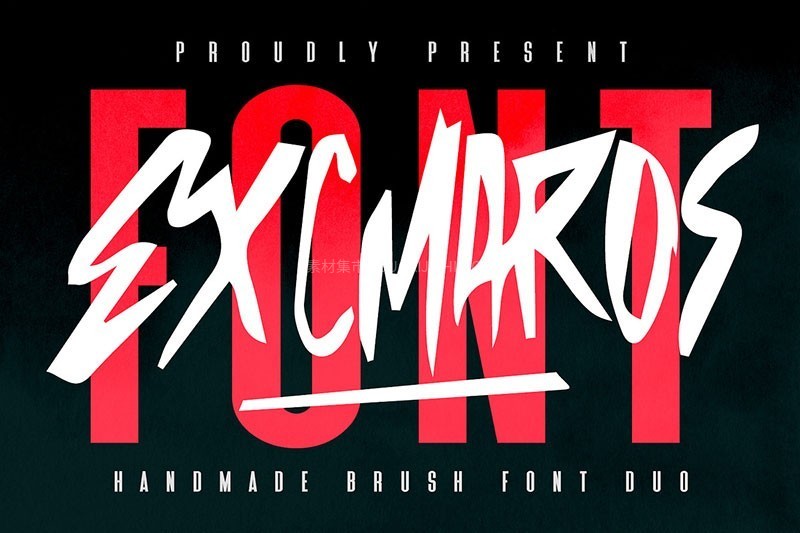
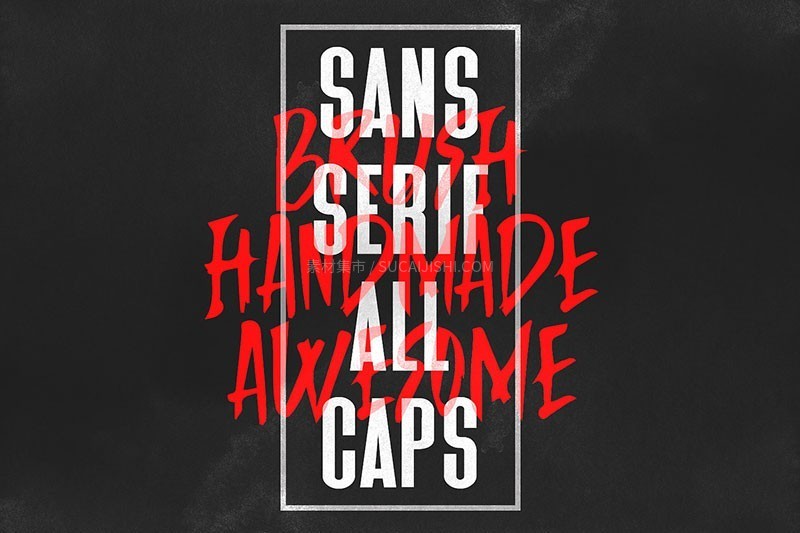
Morthano
一款俏皮的组合字体,将活泼的活力与现代的多功能性完美融合。Morthano 大小写字母是两种风格,将趣味、创意和风格融为一体,浑然一体。Morthano 非常适合品牌推广、包装、海报、社交媒体图形、儿童项目以及任何需要友好、乐观基调的场合,它能为任何视觉呈现瞬间注入活力。
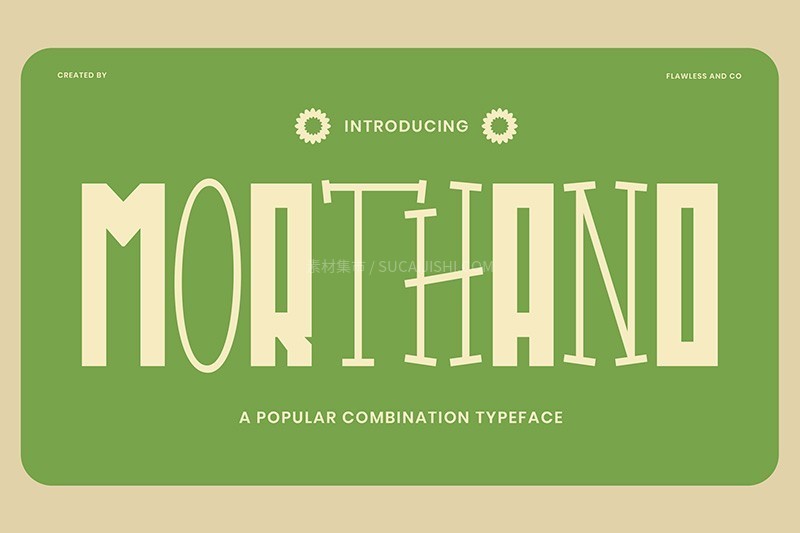
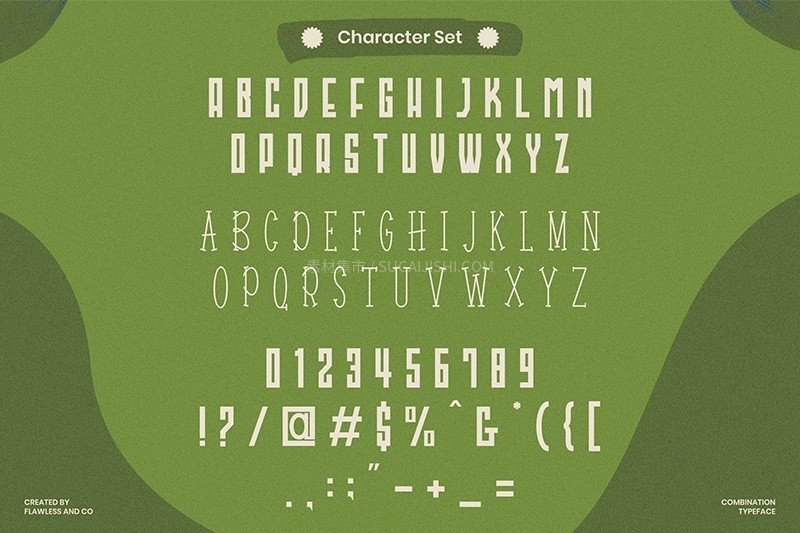
Nineties Party Club
一款大胆的复古字体组合,融合了醒目的无衬线字体和粗体、充满活力的文字。这种强大的组合营造出一种趣味十足的怀旧氛围,非常适合那些以复古风格吸引眼球的设计。
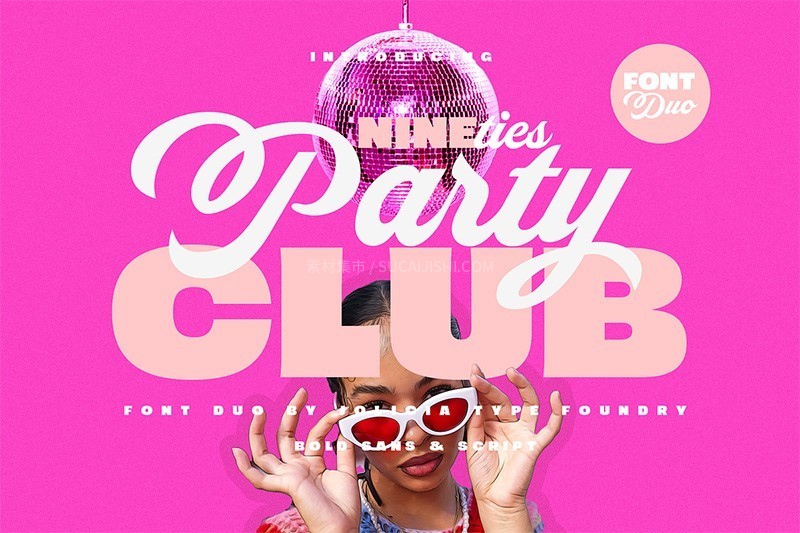
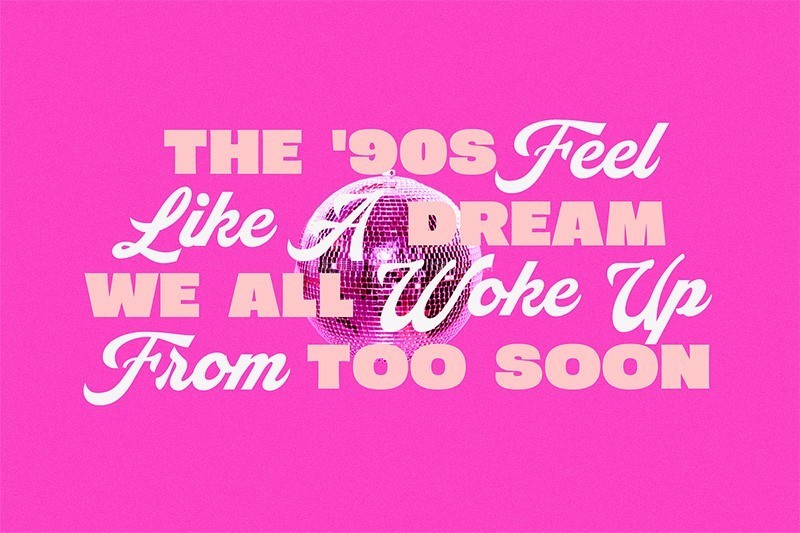
Gatsby Prelude
一款高大字体组合,巧妙融合了装饰艺术风格的无衬线体和单线体。这套字体组合用途广泛,用于从标识到婚礼请柬,也非常适合品牌推广和引言,能为您的设计增添独特的复古魅力。
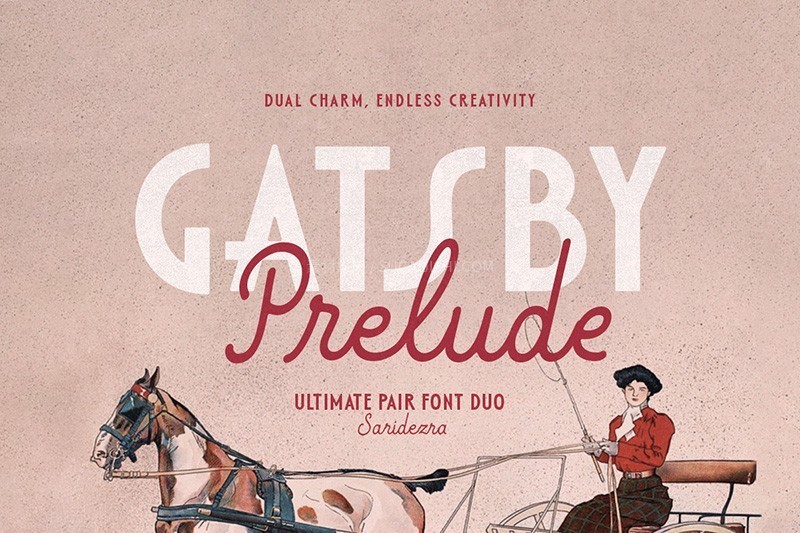
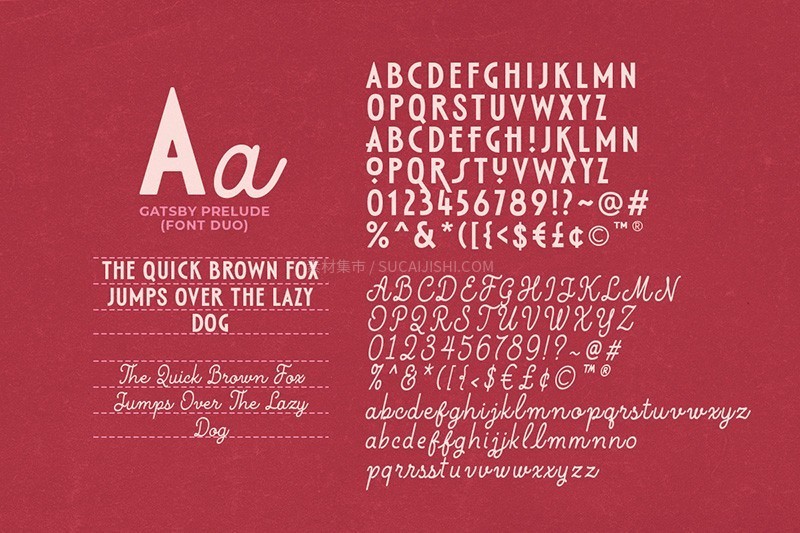
Folkies Vantage
Folkies Vantage 字体粗犷,复古纹理,边缘做旧,营造出一种年代感和灵魂感。它非常适合用于标签、T 恤印花、咖啡馆菜单、标识、乡村风包装以及怀旧设计主题。无论您是为复古牛仔品牌、手工酿造咖啡店还是本地摩托车修理厂创作,这款字体都能以原始的手工质感提升您的品牌形象。
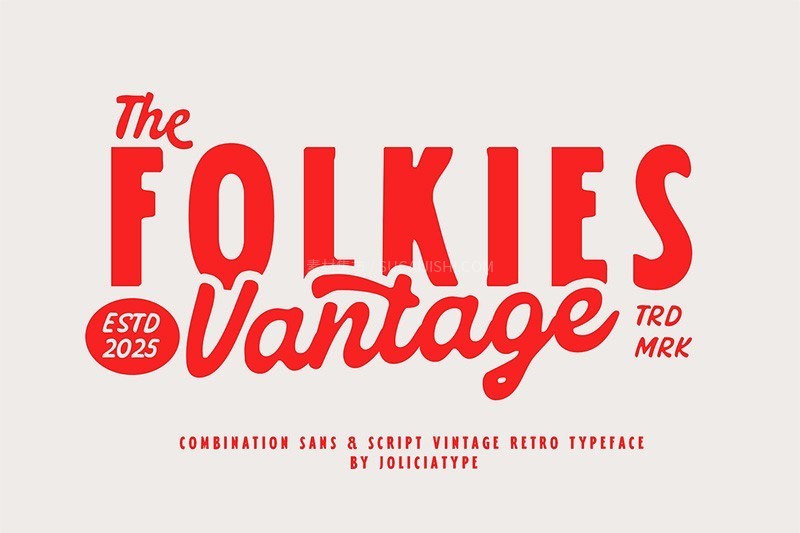
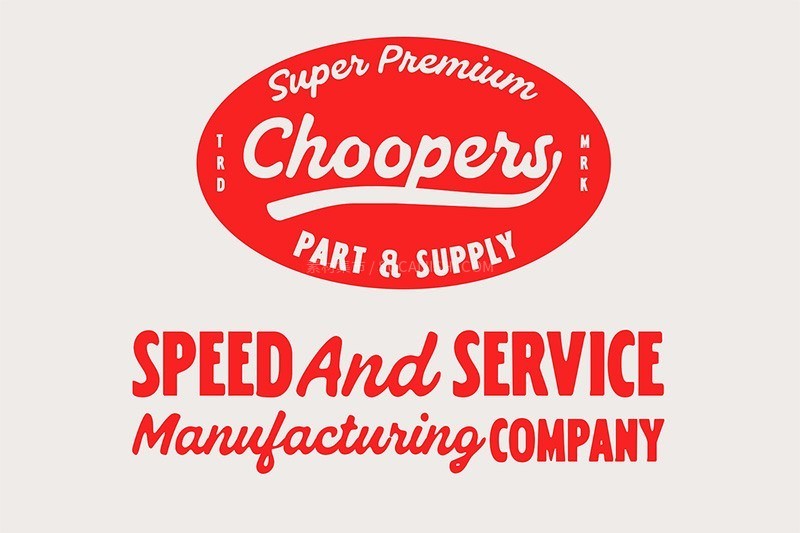
Paris Signature
一款奢华的衬线字体,也是一款优美流畅的手写体。无论是和谐地搭配,还是独立成篇,这套字体都能为任何项目增添精致感,从品牌推广、编辑到婚礼请柬和包装设计。
Vintage Scratches
一款自带复古气息的组合字体,结合了手写体和无衬线体的风格,为任何项目增添了经典和优雅的气息。
Montpier
一款由两种互补字体组合而成的字体家族:一款衬线字体和一款签名脚本字体,旨在和谐地搭配使用。
Pricemart
两种风格迥异但互补的字体:粗体大写无衬线字体和奇思妙想的流畅手写体。这对组合非常适合各种创意设计,能为您的作品注入独特的魅力。
Hearth & Harvest Rustic
一款手绘的衬线和脚本字体家族,带有质朴的风格。它包含两种衬线字体(常规和粗体)以及一款简约的脚本字体,非常适合用于标志、引语、服装、杂志等设计。